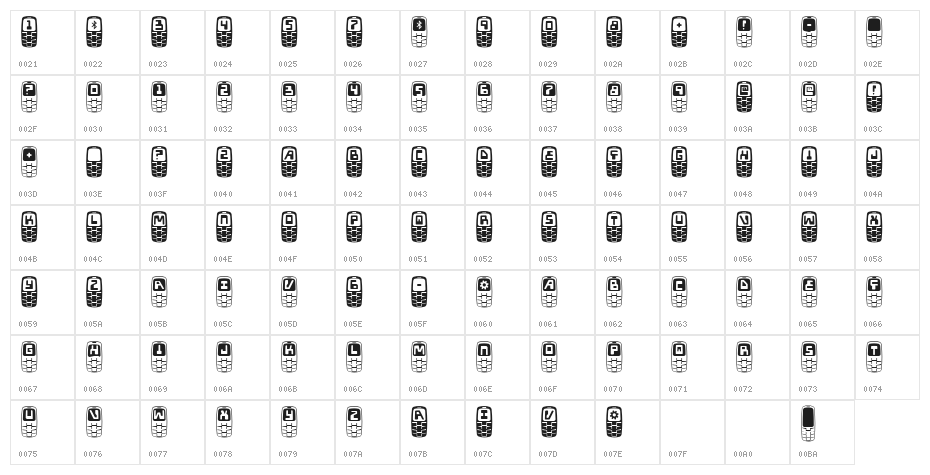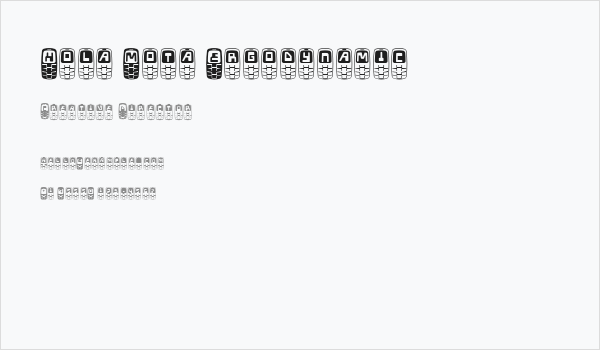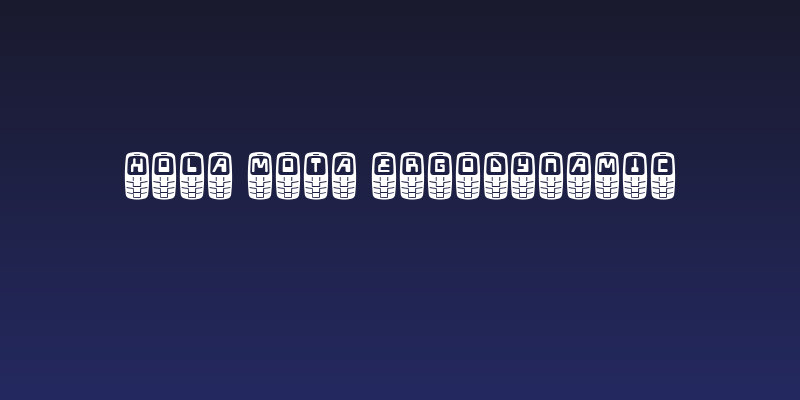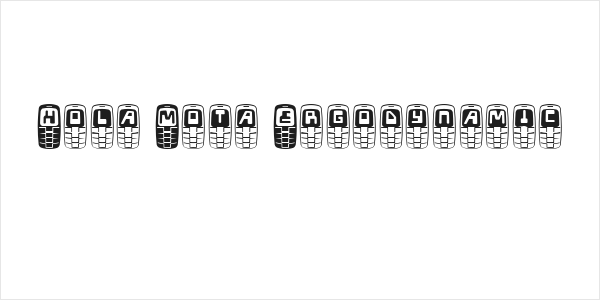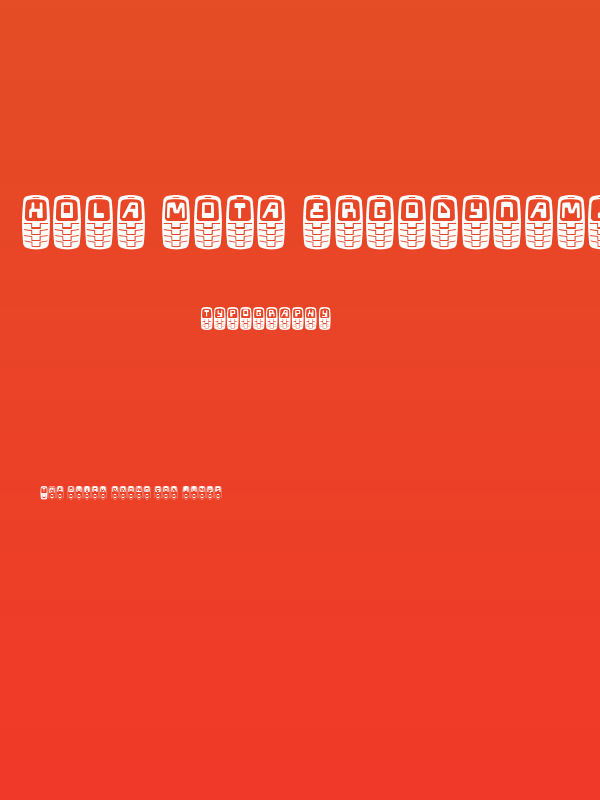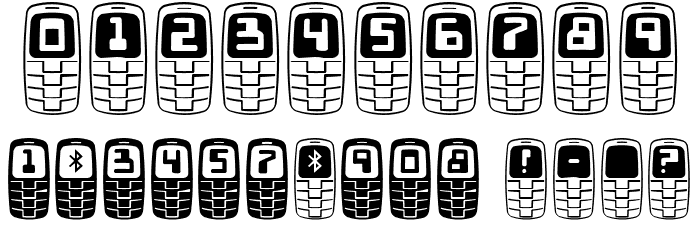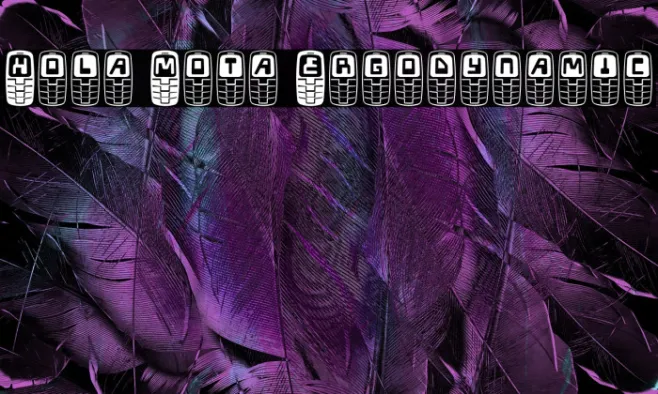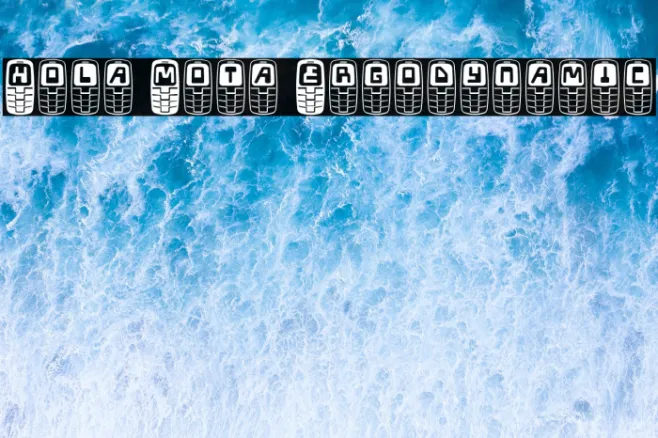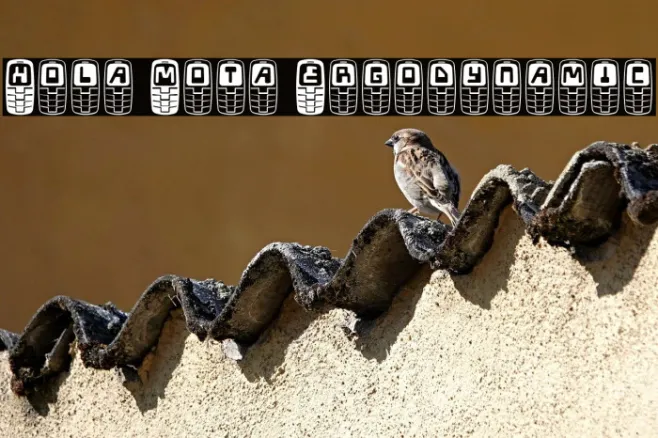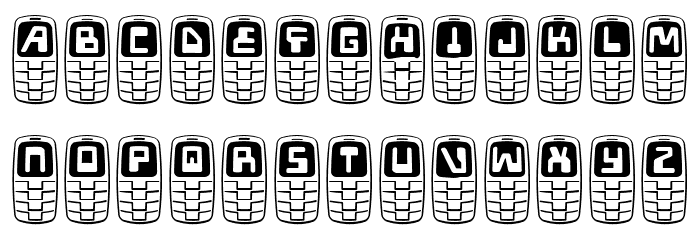
Hola Mota Ergodynamic Font
| Cas d'utilisation | Logos, Posters, Digital Art |
| Projets proposés | Ideal for tech-themed posters, video game graphics, digital art projects, and retro-futuristic branding. |